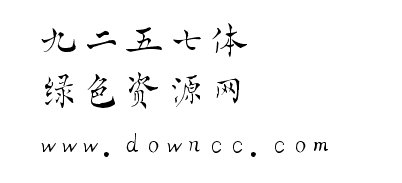
九二五七體字體
九二五七體是喻東山創(chuàng)作的一款個性手寫書法字體,造型優(yōu)雅,兼具毛筆書法字體的飄逸、顏體的秀美,給你高潔大氣的視覺呈現(xiàn),喜歡的朋友就來綠色資源網(wǎng)免費下載吧!
九二五七字體特色
九二五七體(毛筆)字庫,有柳體的秀逸,顏體的彈性,褚體的纖細,歐體像左上的挺拔。
九二五七體別具一格,字跡飄逸灑脫,結(jié)構(gòu)寬松得體,行筆流暢而筆觸凌厲張揚,具有不錯的古風韻味,給你的平面設(shè)計、海報設(shè)計、包裝設(shè)計等帶來不錯的藝術(shù)體驗!